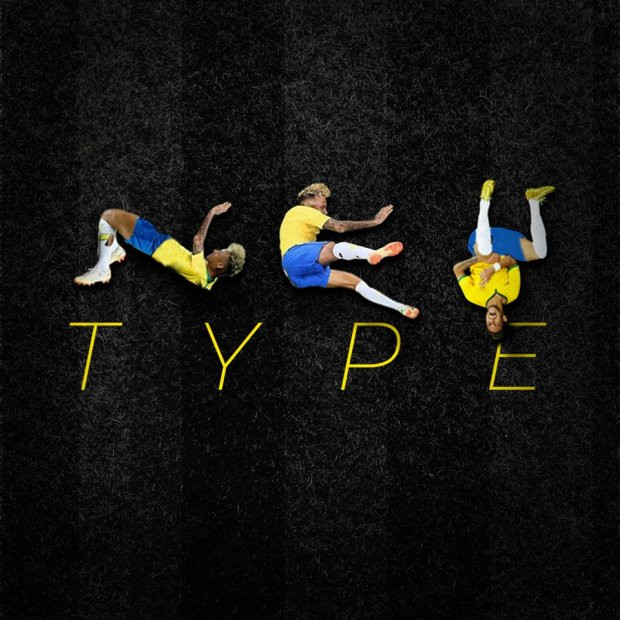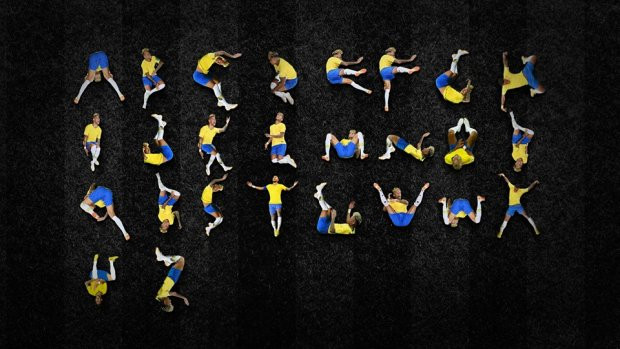
Nếu ở World Cup 2018 có một “diễn viên” thi đấu, người đó đích thị là Neymar. Đó là điều mà rất nhiều cổ động viên nói vui sau khi tiếng còi mãn cuộc giải bóng đá lớn nhất hành tinh trên đất Nga vang lên. Thực tế, theo thống kê, Neymar là một trong những cầu thủ bị phạm lỗi nhiều nhất tại World Cup. Dĩ nhiên, không ít tình huống cầu thủ tài năng này bị phạm lỗi là cực kì rõ ràng nhưng cũng có những tình huống người ta cho rằng Neymar "diễn".
Dẫu sao đi nữa, một thống kê từng được đưa ra cho biết chỉ trong vòng bốn trận tại World Cup 2018, Neymar đã nằm sân tới 14 phút cùng vô số tư thế lăn lộn đã trở thành một biểu tượng và những hình ảnh không thể quên tại World Cup năm nay. Vì thế, một Giám đốc Nghệ thuật người Brazil đang làm việc tại công ty Mutato đã tạo ra một bảng chữ cái (bao gồm 26 chữ cái) lấy cảm hứng từ những pha lăn lộn đặc sắc và đầy nghệ thuật của Neymar. Anh gọi bảng chữ cái này là “Ney Type”.
Chia sẻ với EuroNews, Luciano Jacob cho biết ý tưởng nảy ra trong anh khi thấy cú ngã của Neymar trong trận đấu thứ hai của Brazil tại World Cup 2018. “Nó nhìn giống một chữ T,” anh chia sẻ. Sau đó, Jacob thực hiện tìm kiếm thêm hình ảnh của Neymar trên Internet và anh nhận ra chỉ với một vài chỉnh sửa bằng Photoshop anh đã có thể tạo ra toàn bộ bảng chữ cái.
“Nó khá khó. Tôi đã tìm trên Internet nhiều cú ngã của Neymar để có thêm các bộ phận tôi cần để tạo ra bảng chữ cái,” anh giải thích. Sau khi đăng tải trên Facebook, bộ font chữ Ney Type nhanh chóng nhận được rất nhiều sự chú ý. “Tôi cảm thấy rất vui. Tôi biết ý tưởng này tiềm năng nhưng không nghĩ là nó tạo ra ảnh hưởng tới vậy,” Jacob nói. Anh thành thực chia sẻ bảng chữ cái này giúp “người khác bật cười” chứ không hề có ý chỉ trích Neymar, dù vậy anh đồng ý rằng hành động của cầu thủ này đôi khi có một chút “kịch tính hoá”.